Font chữ có chân (serif font) là font có chân chữ nhỏ ở đầu và cuối nét, mang phong cách cổ điển, sang trọng được sử dụng rộng rãi trong thiết kế bao bì cao cấp, catalogue thời trang và in ấn cho thương hiệu luxury. Phông chữ có chân với đặc điểm thanh lịch, đáng tin tạo cảm giác chuyên nghiệp, uy tín.
Font chữ có chân là gì?
Font chữ có chân (serif font) là font có các chân chữ (serif) – những nét nhỏ ở đầu và cuối nét chính. Serif ra đời từ thời La Mã cổ đại, là di sản của nghệ thuật khắc chữ trên đá.
Tại sao có chân chữ: Ban đầu, thợ khắc chữ trên đá dùng đục và búa. Khi kết thúc một nét, họ phải tạo một nét nhỏ vuông góc để “hoàn thiện” nét chính – đó là nguồn gốc của serif.
Phân loại font serif:
- Old Style Serif (cổ điển): Serif bo tròn, tương phản nét đậm-mảnh nhẹ. Ví dụ: Garamond, Caslon. Cảm giác: cổ điển, văn học, học thuật.
- Transitional Serif (chuyển tiếp): Giữa Old Style và Modern. Ví dụ: Times New Roman, Baskerville. Cảm giác: chuyên nghiệp, tin cậy.
- Modern Serif (hiện đại): Serif mỏng như tóc, tương phản nét cực mạnh. Ví dụ: Didot, Bodoni. Cảm giác: sang trọng, thời trang, luxury.
- Slab Serif (serif đậm): Serif dày như nét chính, blocky. Ví dụ: Rockwell, Courier. Cảm giác: mạnh mẽ, retro, typewriter.
Ưu điểm font có chân:
- Sang trọng, cao cấp: Serif tạo cảm giác lịch lãm, quý phái – lý do Vogue, Dior, Chanel đều dùng serif.
- Đáng tin cậy, uy tín: Serif gợi liên tưởng đến sách cổ, báo chí truyền thống, văn bản chính thức – tạo niềm tin.
- Dễ đọc trong in ấn: Chân chữ giúp mắt dễ theo dõi dòng chữ khi đọc văn bản dài in trên giấy.
- Timeless – vượt thời gian: Serif tồn tại hơn 500 năm, không bao giờ lỗi mốt.
Bảng tổng hợp font chữ có chân sang trọng việt hóa như sau:
Tên font |
Loại serif |
Ứng dụng in ấn |
Playfair Display |
Modern/Transitional, elegant | Bao bì thời trang, mỹ phẩm luxury |
Libre Baskerville |
Transitional, classic | Catalogue cao cấp, annual report |
Merriweather |
Old Style, dễ đọc | Brochure, body text sách, tạp chí |
Cormorant |
Modern, elegant display | Logo thời trang, thiệp cưới cao cấp |
Libre Bodoni |
Modern, high contrast | Bao bì mỹ phẩm, magazine fashion |
Crimson Text |
Old Style, văn học | Sách, novel, văn bản dài |
Lora |
Modern brushed, contemporary | Brochure lifestyle, catalogue organic |
EB Garamond |
Old Style, cổ điển Renaissance | Sách cổ điển, văn bản học thuật |
Cinzel |
Roman capitals, uy nghi | Logo luật sư, ngân hàng, tài chính |
Vollkorn |
Old Style, dễ đọc print | Body text catalogue, brochure |
Ứng dụng font có chân trong bao bì cao cấp
Font có chân với phong cách sang trọng được ưa chuộng:
- Tạo cảm giác luxury, high-end: Serif là “uniform” của thương hiệu cao cấp – Vogue dùng Didot, Dior dùng serif custom – liên tưởng mạnh mẽ đến luxury.
- Đáng tin cậy, uy tín: Banks, law firms, universities đều dùng serif vì tạo cảm giác established, trustworthy.
- Timeless, không lỗi mốt: Serif tồn tại 500+ năm, thiết kế dùng serif từ 50 năm trước vẫn elegant ngày nay.
- Feminine, elegant: Modern serif (Didot-style) đặc biệt phù hợp thương hiệu nữ tính, thanh lịch.
Font có chân xuất hiện trong nhiều sản phẩm in ấn:
- Bao bì mỹ phẩm luxury: nước hoa, skincare cao cấp, makeup premium.
- Túi giấy thời trang: boutique, designer brand, haute couture shop.
- Bao bì rượu vang: wine label, whiskey box, spirits packaging.
- Catalogue thời trang: lookbook, collection book fashion brand.
- Thiệp cưới cao cấp: wedding invitation, save the date elegant.
- Menu fine dining: Michelin restaurant, luxury hotel dining.
- Brochure bất động sản cao cấp: luxury condo, villa, resort.
- Certificate, diploma: bằng khen, giấy chứng nhận trang trọng.
- Bao bì chocolate cao cấp: artisan chocolate, premium confectionery.
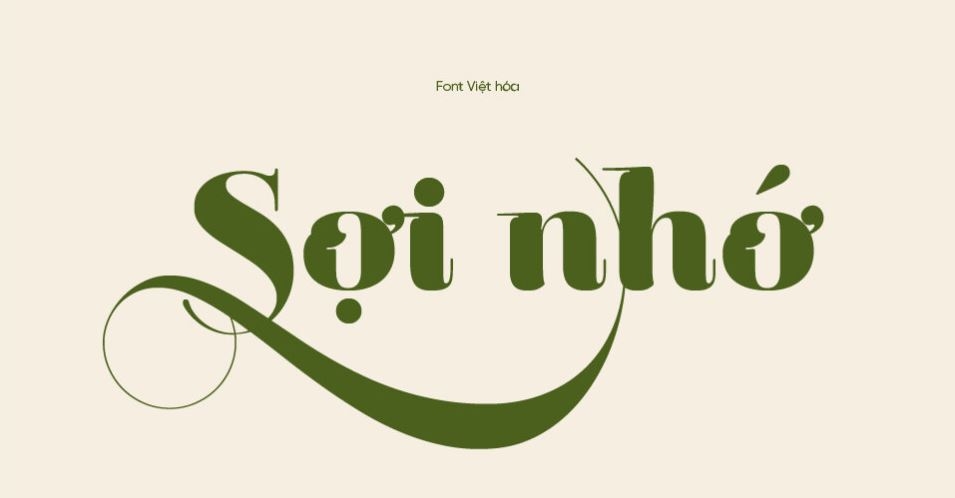
3. Serif hay Sans-serif cho bao bì?
Tùy ngành: Luxury/fashion/wine → Serif. Tech/modern/casual → Sans-serif. Premium food có thể dùng cả hai: serif cho tên sản phẩm (elegant), sans cho thông tin (readable).
Font chữ có chân sang trọng, đáng tin, timeless – lý tưởng cho bao bì cao cấp, thời trang, luxury. Tải miễn phí từ Google Fonts.